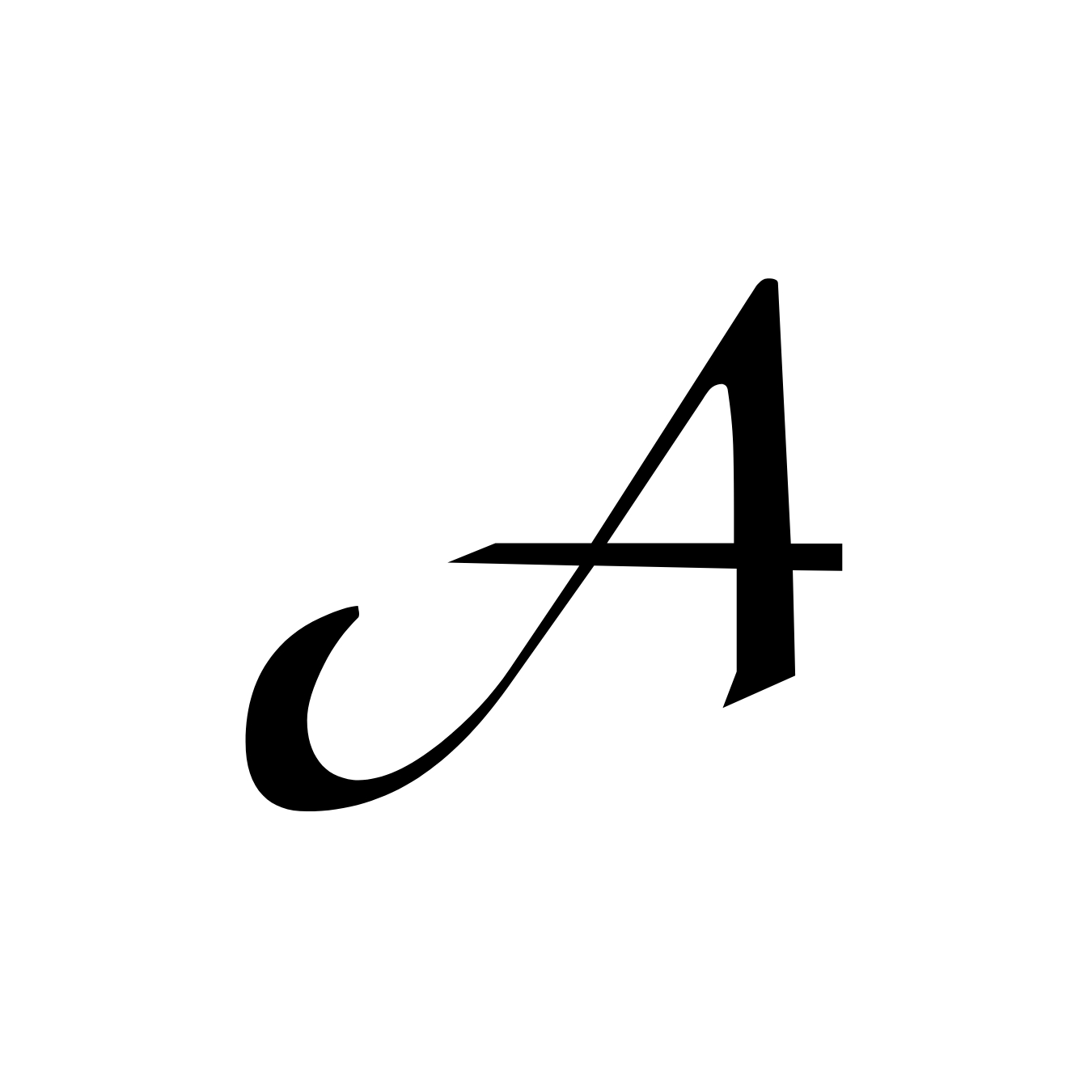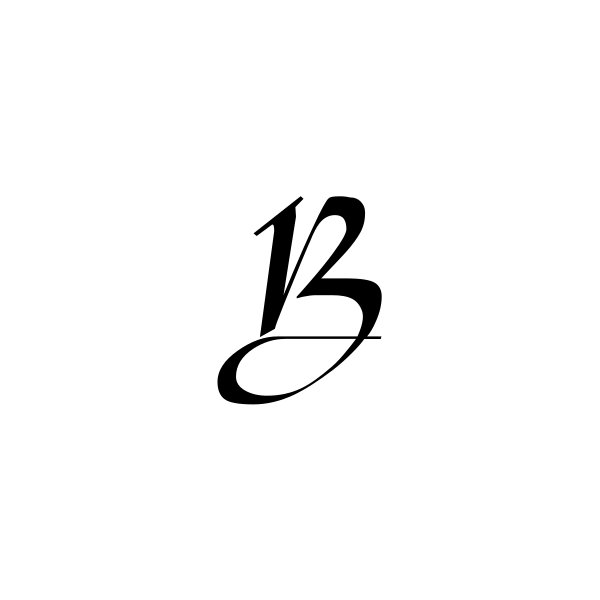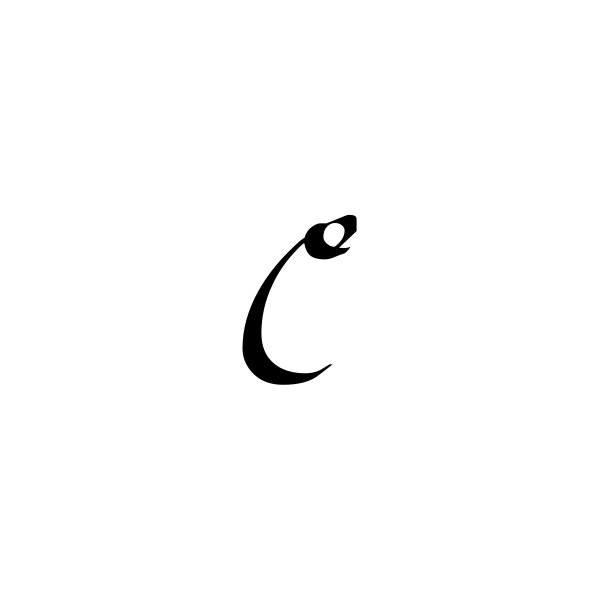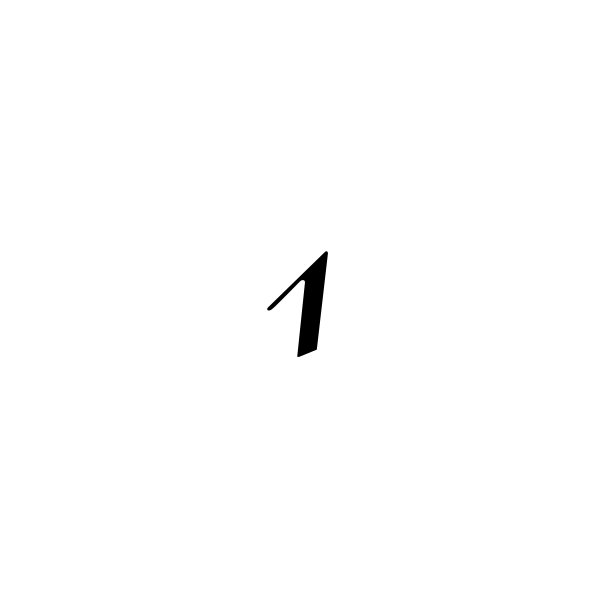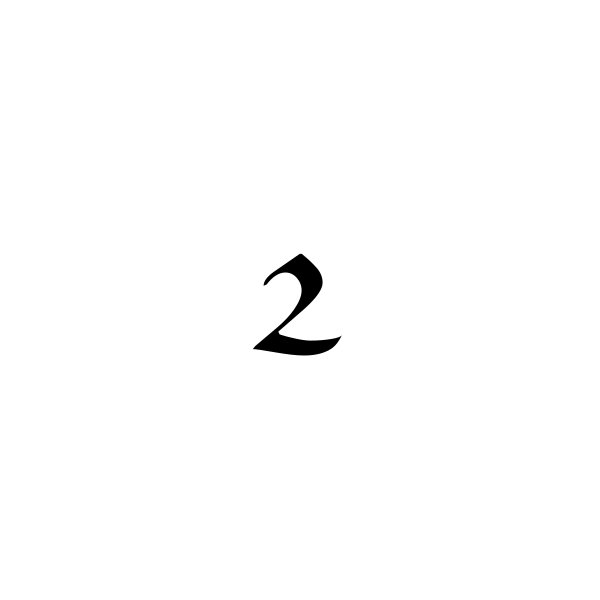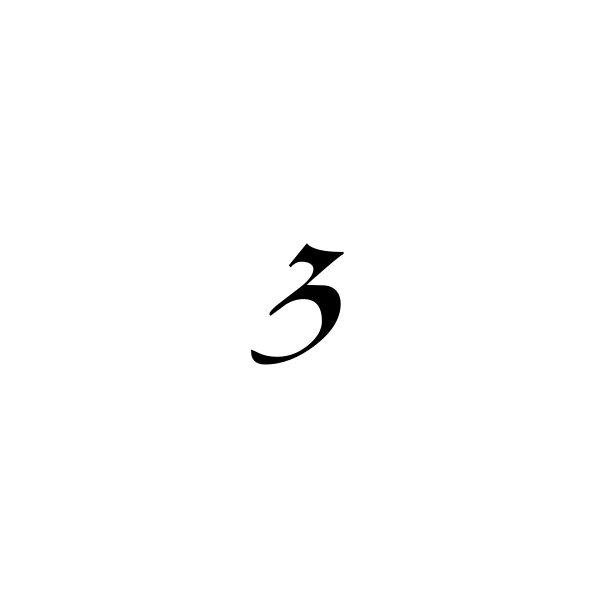
- Die Sultan’s Treasure Monogramm Schriftart ist eine dekorative Schrift, inspiriert von klassischen ornamentalen Schriftstilen aus dem Nahen Osten. Die Buchstaben besitzen weiche Kurven, elegante Linien und charakteristische Formen, die dem Alphabet eine raffinierte und leicht exotische Ausstrahlung verleihen. Gleichzeitig bleiben die Zeichen klar und ausgewogen gestaltet, sodass sie sich gut für Schneide- und Druckprojekte eignen.
Die Schrift enthält Grossbuchstaben, Kleinbuchstaben und Zahlen, wodurch ein vollständiger Zeichensatz für personalisierte Designs entsteht. Durch ihre dekorative Gestaltung eignet sie sich besonders gut für Monogramm-Projekte, individuelle Namen, dekorative Schriftzüge und thematische Bastelarbeiten, bei denen ein stilvoller und ornamentaler Look gewünscht ist.
Dank der fliessenden Formen und klar definierten Linien lässt sich die Schrift sauber mit Plottern und anderen Bastelmaschinen schneiden, wodurch sie sich für viele kreative Anwendungen eignet.